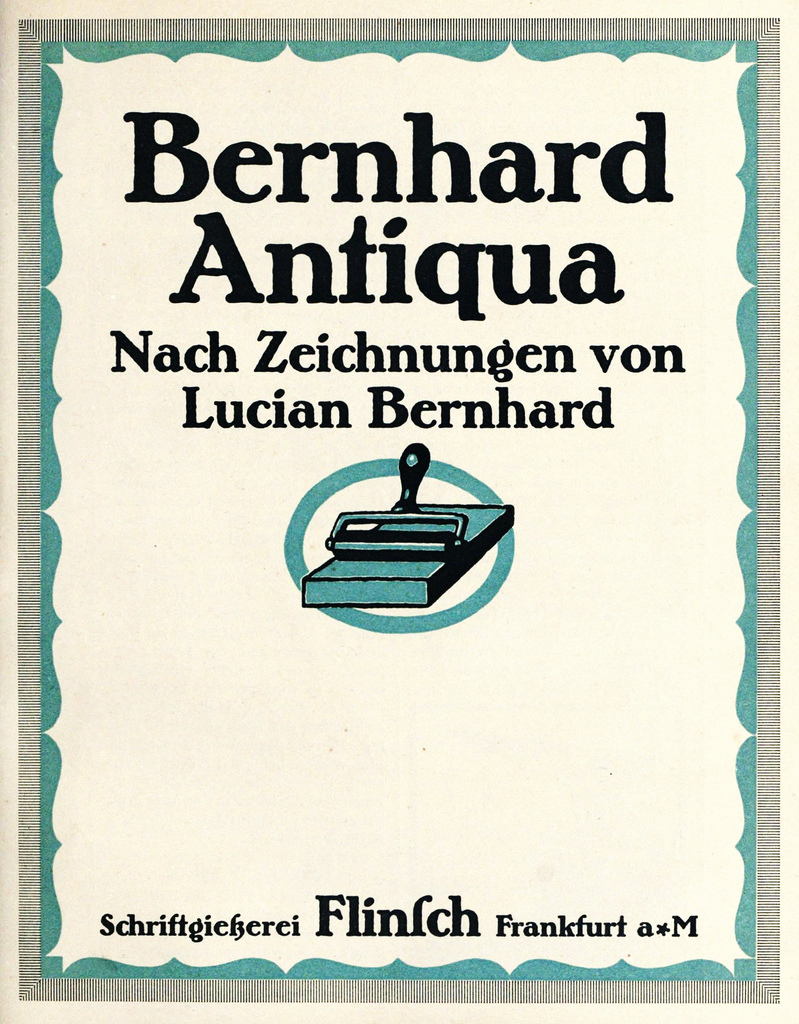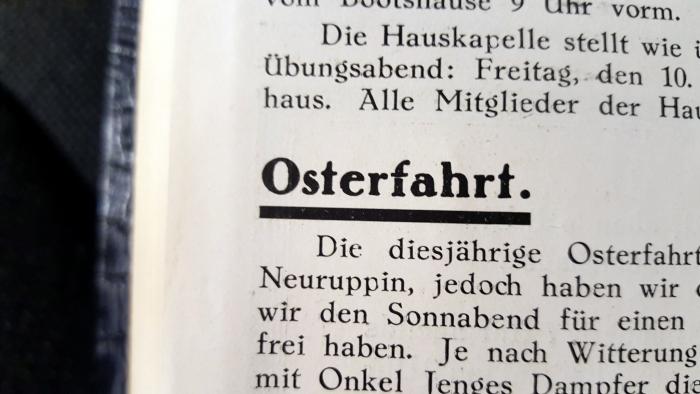
[Mitglied oldf…] Geschrieben Januar 30, 2016 Teilen Geschrieben Januar 30, 2016 Hallo zusammen, ich suche die Schriftart, die in unserer Vereinszeitschrift in den 1920er und 1930er Jahren verwendet wurde. Das Fotos stammt von der Ausgabe 1932 RC Nordstern Berlin (Rudern). Wer kennt die Bezeichnung dieser Schriftart? Bei Bedarf kann ich weitere Beispiele liefern... Viele Grüße Karsten Link zu diesem Kommentar
Beste Antwort [Mitglied catf…] Geschrieben Januar 30, 2016 Beste Antwort Teilen Geschrieben Januar 30, 2016 Alt-Mediäval von M. Hertwig, bei H. Berthold A.G. 1915 erschienen. Nach dem g könnte es die Textschrift sein. Leider hab ich nur diesesa Hamburgers zum Vergleich. Dann fand ich noch einen recht alten Strang hier: http://www.typografie.info/3/topic/26747-bleisatzschrift-aus-privatdruck-1938-heidelberg-knifflig/ und die Schrift wirkt für mich nahezu identisch, und wurde damals auch als Alt-Mediäval erkannt. Anscheinend hat auf Gutenbergers Angebot damals keiner reagiert. Also: Digital? Nein. Ich war zwar 2012 auch schon hier, aber deutlich weniger aktiv. 1 Link zu diesem Kommentar
[Mitglied Vitr…] Geschrieben Januar 30, 2016 Teilen Geschrieben Januar 30, 2016 Auf luc.devroye.org im Artikel über Max Hertwig fand ich noch ein paar Schriftmuster der Alt-Mediäval. Link zu diesem Kommentar
[Mitglied catf…] Geschrieben Januar 30, 2016 Teilen Geschrieben Januar 30, 2016 Nun möchte ich diese Schrift gerne am PC verwenden. Hast Du einen Tipp, wo man die Schriftart kaufen bzw. downloaden kann?Grüß oldfield Tja, und das ist ja gerade der Haken bei vielen alten Bleischriften. Sie wurden nie digitalisiert, und möchte man dies machen, kommt man oft nicht an ein komplettes Figurenverzeichnis. Also, da du ja schon doppelt nachfragst: Nein, gibt es nicht. Weder zum einfach so herubnterladen - was ja erst einmal viele Arbeitsstunden zum digitalisieren wäre - inkl der dann ja noch nötigen Arbeiten an den Fontdaten, die man eben nur sieht, hat man sich die Arbeit nicht gemacht - und bei einer Brotschrift wie dieser sitzt man deutlich länger dran, als bei einer Displayschrift in der man zumeist nur eine Überschrift setzt, noch gegen Geld zu lizensieren. Und da warten wohl noch hunderte alter Schriften, nicht in Vergessenheit zu geraten. Link zu diesem Kommentar
[Mitglied Stef…] Geschrieben Januar 31, 2016 Teilen Geschrieben Januar 31, 2016 Falls eine Schrift mit ähnlicher Anmutung benötigt wird, solltest du dir die Henriette anschauen. 1 Link zu diesem Kommentar
[Mitglied gute…] Geschrieben Januar 31, 2016 Teilen Geschrieben Januar 31, 2016 Naja, die ist schon ziemlich weit weg ... Link zu diesem Kommentar
[Mitglied Stef…] Geschrieben Januar 31, 2016 Teilen Geschrieben Januar 31, 2016 Naja, was wäre dein Alternativvorschlag? Link zu diesem Kommentar
[Mitglied oldf…] Geschrieben Januar 31, 2016 Themen-Ersteller Teilen Geschrieben Januar 31, 2016 Ja! "Henriette black" passt super als Überschrift! War auch kostenlos bei Myfonts.com erhältlich Jetzt fehlt nur die Schriftart für den Text nach der Überschrift. Besonders die Punkte, die als Rauten dargestellt werden, haben es mir angetan. Unter "Textschrift" habe ich nichts gefunden. Kann mir hier noch jemand weiterhelfen? Link zu diesem Kommentar
[Mitglied catf…] Geschrieben Januar 31, 2016 Teilen Geschrieben Januar 31, 2016 Das ist ja gerade die normale Alt-Mediäval, die es ja leider digital nicht gibt. 1 Link zu diesem Kommentar
[Mitglied oldf…] Geschrieben Januar 31, 2016 Themen-Ersteller Teilen Geschrieben Januar 31, 2016 ok, aber gibt des denn eine verfügbare ähnliche Schrift? Link zu diesem Kommentar
[Mitglied ea3d…] Geschrieben Januar 31, 2016 Teilen Geschrieben Januar 31, 2016 bei MyFonts herunterladen Link zu diesem Kommentar
[Mitglied oldf…] Geschrieben Januar 31, 2016 Themen-Ersteller Teilen Geschrieben Januar 31, 2016 danke ...das kommt dem schon recht nahe. Noch jemand eine Idee? Link zu diesem Kommentar
[Mitglied Uwe…] Geschrieben Februar 6, 2016 Teilen Geschrieben Februar 6, 2016 Hallo, die Überschrift „Osterfahrt“ ist eine andere Schrift wie die Brotschrift. Die Überschrift sollte aus dieser Ecke kommen: Quelle: https://www.flickr.com/photos/double-m2/5219056973 Blöderweise findet man in digitaler Form idR nur die Condensed ... Hier mal ein Link ... http://www.identifont.com/show?HA Bernhard A revival of Bernhard Condensed, designed by Lucian Bernhard and originally published by Bauer Type Foundry in 1912. Designers: Lucian Bernhard and Tatiana Lyskova Year: 1912,1993 Publisher: ParaType Es gibt auch Versionen von Bitstream, Elsner+Flake, ... aber alles die Schmalen ... MfG Link zu diesem Kommentar